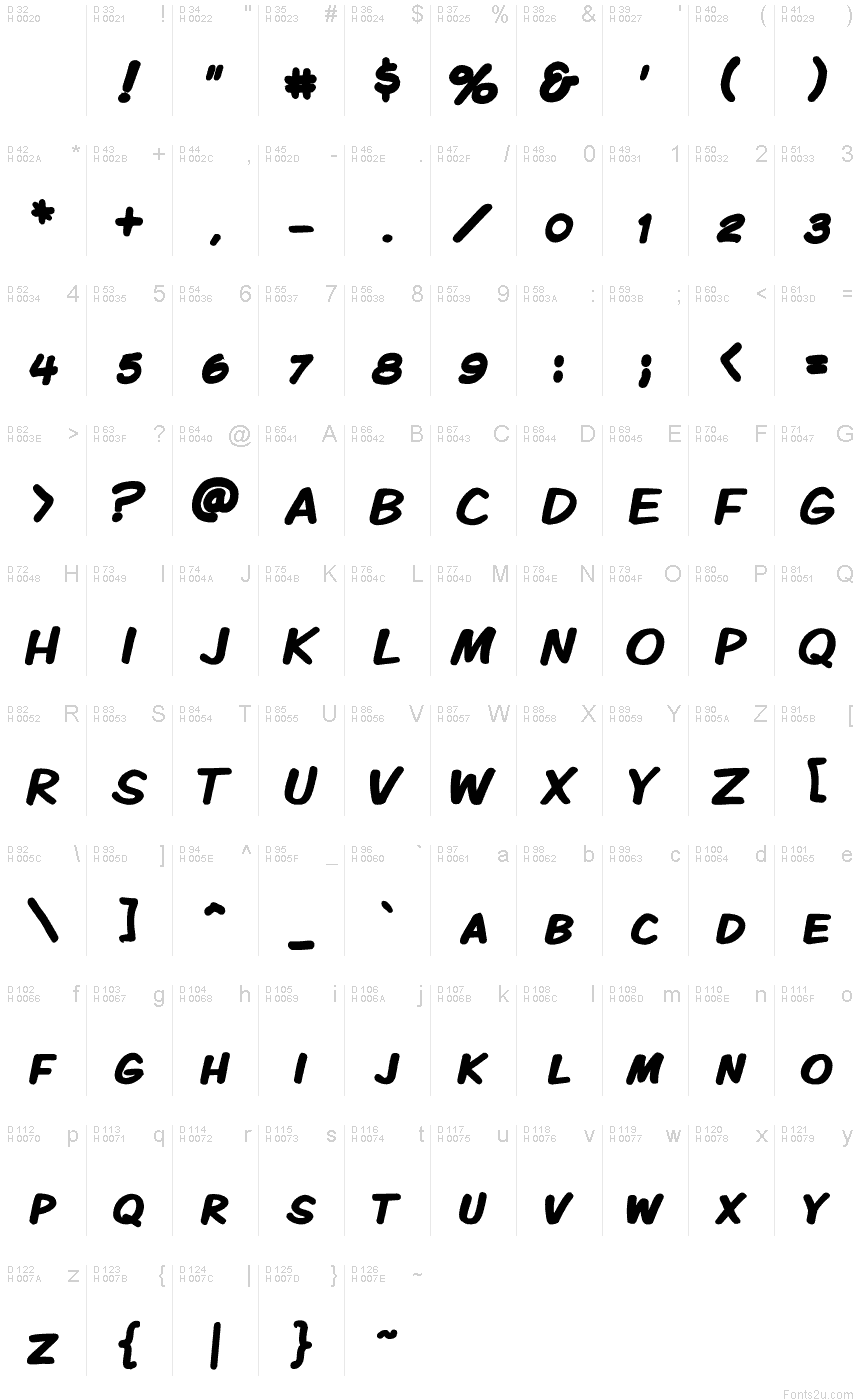
Komika Display Kaps Bold autorstwa Wolfbainx & Apostrophic Labs to darmowy krój typu display do komiksów, który idealnie balansuje między masywnym charakterem a czystą czytelnością. Grube, nasycone kreski i lekko pochylone litery sprawiają wrażenie rysowanych grubym markerem, nadając Twoim słowom głośny, przyjazny ton zamiast nieśmiałego szeptu. Konstrukcja oparta na wielkich literach sprawia, że wszystko wygląda wyraziście i dynamicznie, dzięki czemu nawet krótkie nagłówki nabierają rangi tytułów.
Użyj Komika Display Kaps Bold w komiksach internetowych, na okładkach książek dla dzieci, w menu gier, plakatach, miniaturach na YouTube czy projektach naklejek, aby dodać im zabawnego, odręcznego pazura bez utraty czytelności. Odstępy są wystarczająco ciasne, by czuć energię, ale na tyle otwarte, by tekst był szybko skanowany na ekranach lub z odległości. Ten darmowy font świetnie sprawdza się w parze z prostym krojem bezszeryfowym w tekście głównym, pozwalając Komice nadać nagłówkom głośnego, pełnego charakteru wyglądu.